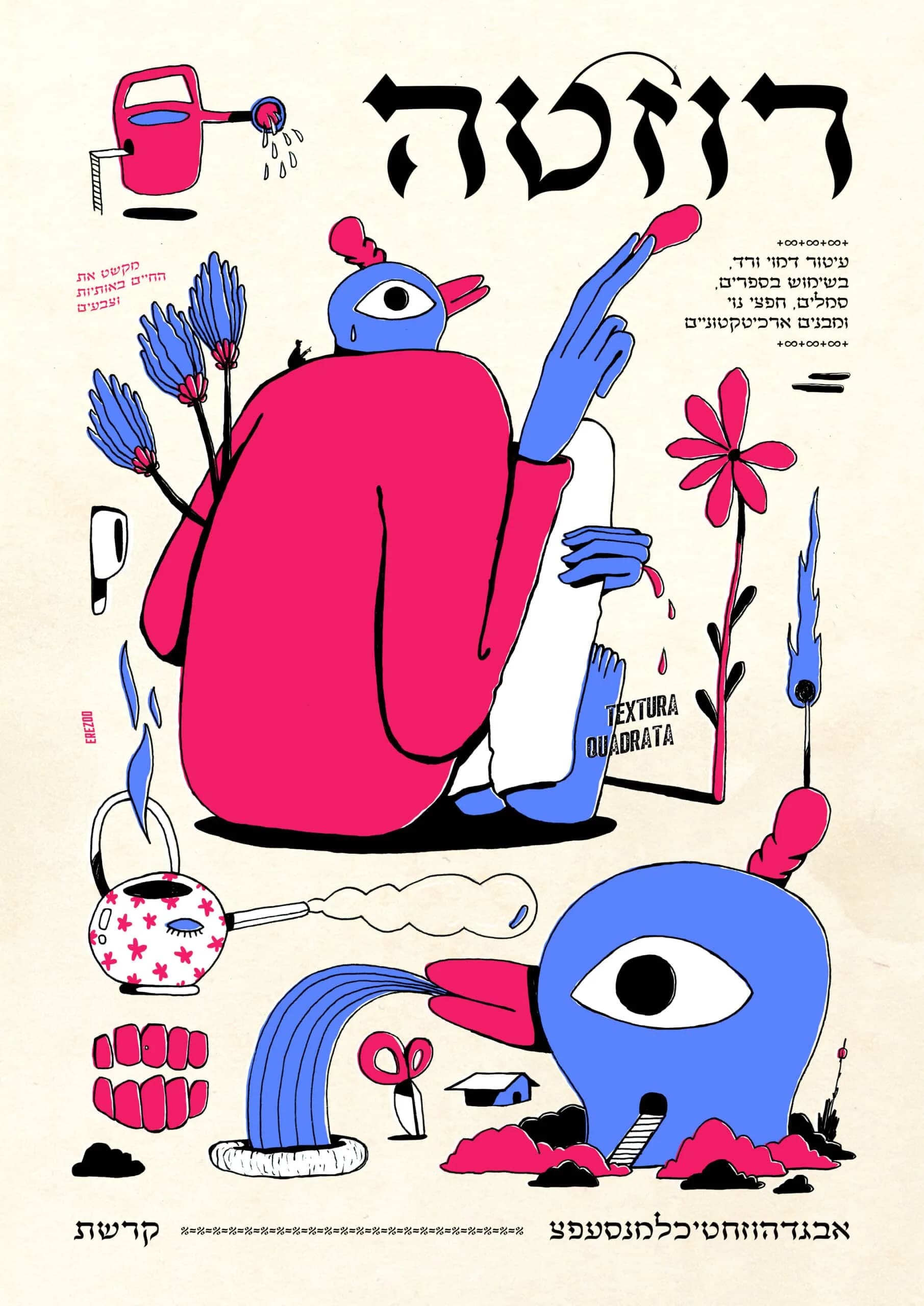
רוזטה תגידו היי לפונט אסתטי וייחודי בקטע אחר! "רוזטה" הוא פונט מכושף בסטייל גותי ובהשראתו של המעצב הגרפי והקליגרף המחונן - פרד פאוקר. הפונט מאופיין בקצוות עבים, קווים אנכיים מעוקלים והמון אופי מתפרץ.